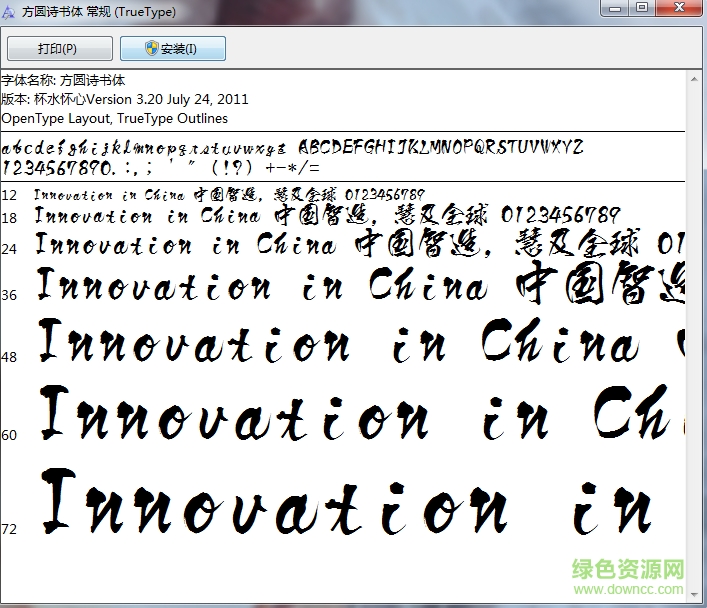
方圓詩(shī)書體是杯水懷心之多一款書法字體,很有毛筆潑墨揮灑之風(fēng),蘊(yùn)含古風(fēng)經(jīng)典之感,流暢連貫給人最佳視覺呈現(xiàn),綠色資源網(wǎng)歡迎大家免費(fèi)下載!
方圓詩(shī)書體是一款手寫創(chuàng)意字體本作品可用于出版印刷字體、廣告設(shè)計(jì)字體、網(wǎng)頁(yè)設(shè)計(jì)字體、包裝設(shè)計(jì)字體、屏幕顯示字體等。
方圓詩(shī)書體是一款繁體字體,部分文字在使用時(shí)可能無(wú)法顯示,需調(diào)整到簡(jiǎn)體狀態(tài),如圖所示的“圓”。